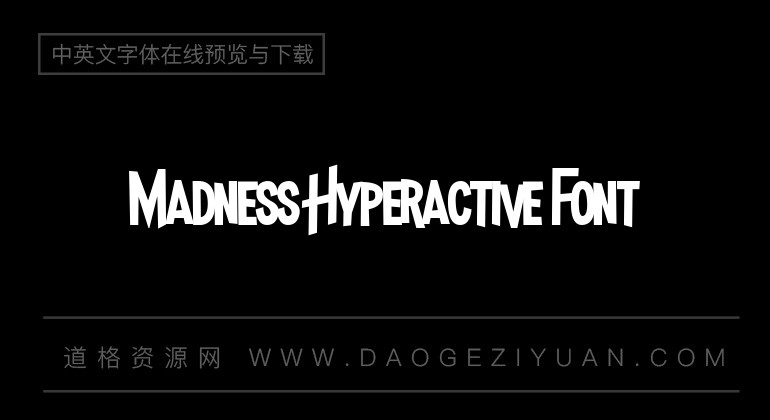
Madness Hyperactive Font
Madness Hyperactive Font是一种非常独特的字体,它的设计风格非常鲜明,适合用于各种标题、海报、广告等需要强烈视觉冲击的设计中。 该字体的特点是字母形状非常扭曲,充满了动感和活力,仿佛每个字母都在不停地跳动、扭曲。字母之间的间距也非常紧凑,让整个文本看起来更加紧凑、有力。 Madness Hyperactive Font适合用于需要表现出激情、能量、创意和年轻感的设计中,比如音乐演唱会、时尚杂志、酒吧、夜店等。使用该字体可以让设计更加引人注目、充满活力。
Madness Hyperactive Font是一款非常不错的手写艺术字体,具有很好的视觉感,适合于文化类的宣传设计、商业类品牌的广告和产品包装设计以及个性化文字排版等较多场景。